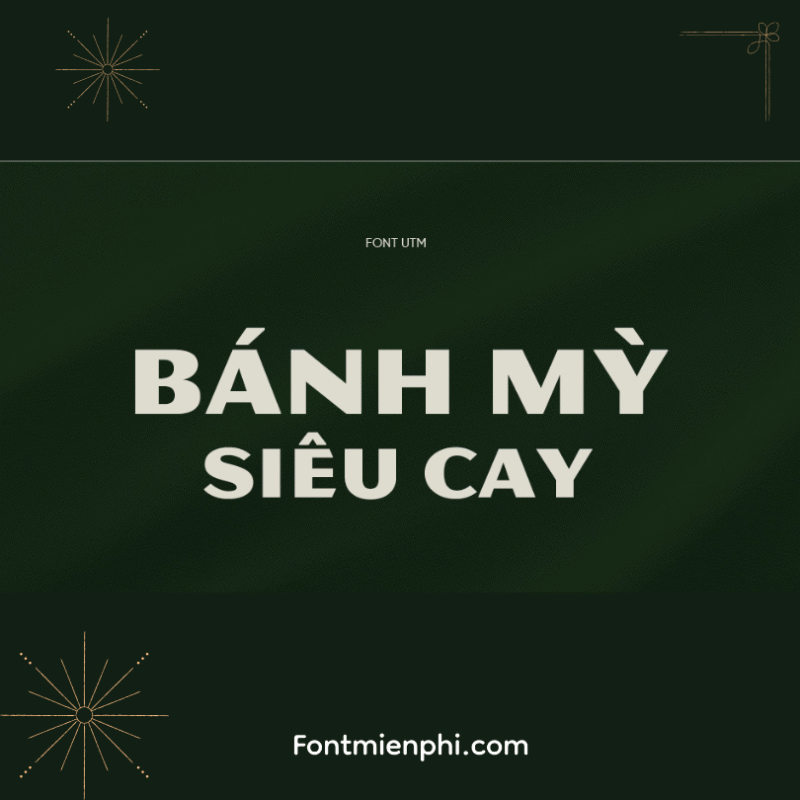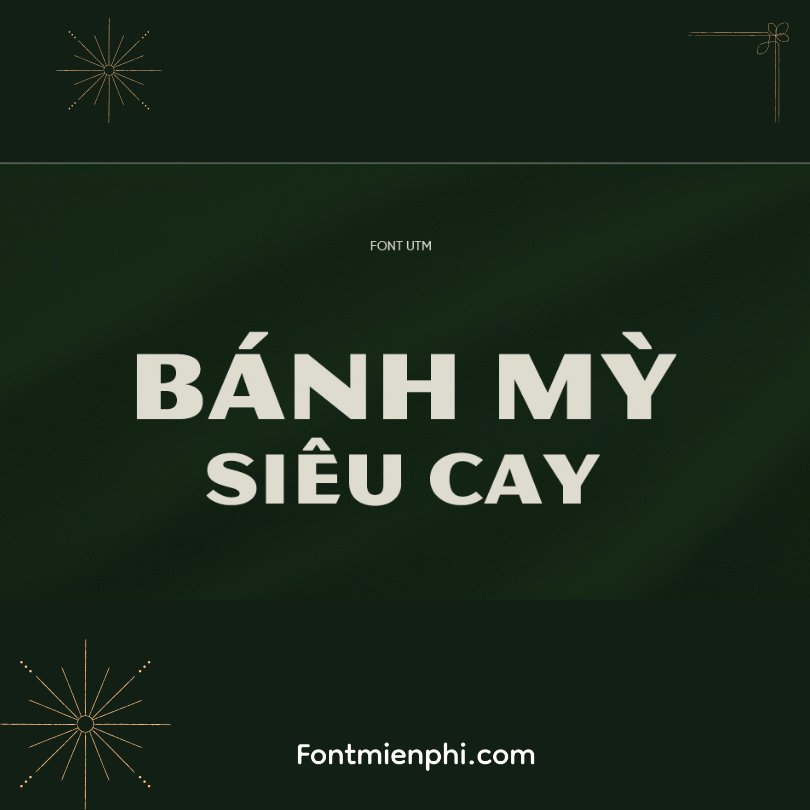
Font Việt hóa UTM Magnesium
Font Việt hóa UTM Magnesium – Nét Chữ Thanh Mảnh Hiện Đại
Giới thiệu:
Font UTM Magnesium đã được Việt hóa hoàn chỉnh, sở hữu nét chữ sans-serif thanh lịch với các đường nét tinh tế, phù hợp cho thiết kế hiện đại từ in ấn đến digital.
Đặc điểm nổi bật:
✔ Thiết kế chữ không chân (sans-serif) sạch sẽ, dễ đọc
✔ Hỗ trợ đầy đủ bộ dấu tiếng Việt
✔ Đa dạng ứng dụng từ web đến in ấn
Ứng dụng lý tưởng:
• Thiết kế logo, branding
• Website và ứng dụng di động
• Tạp chí, ấn phẩm thời trang
• Bao bì sản phẩm cao cấp